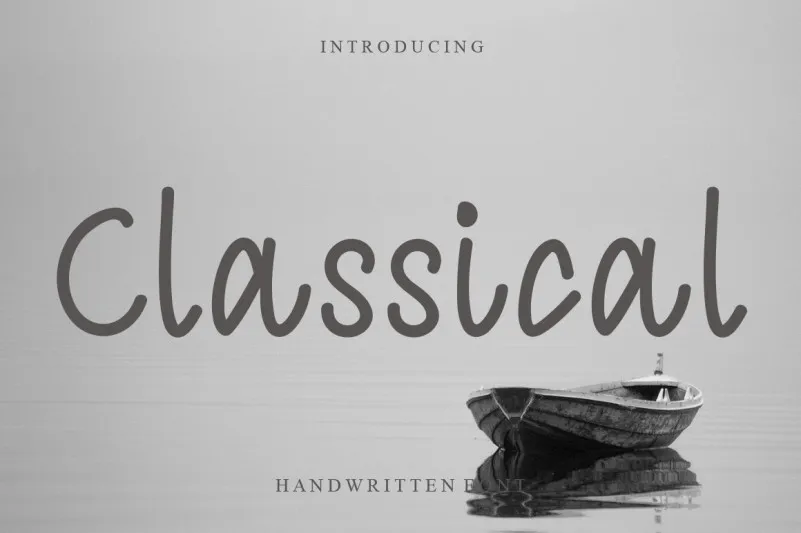
Classical Font – Download Grátis
Esta é uma fonte feita para aqueles que apreciam os detalhes mínimos e a delicadeza dos traços cínticos. Com seu estilo elegante e fininho, esta fonte é ideal para designers que buscam um toque único nas suas criações. Ela se destaca em diversas ideias de design, trazendo uma nota de levejão e simplicidade a cada projeto. A sua natureza delicada e suave tornará qualquer layout ou arte mais encantador e atraente. Para quem busca deixar seus projetos ainda mais belos, esta fonte é um verdadeiro tesouro. Sem dúvida, ela se adequa perfeitamente para design de rótulos de produtos, editoração de livros, e até mesmo para criar mensagens singelas nos arquivos pessoais.